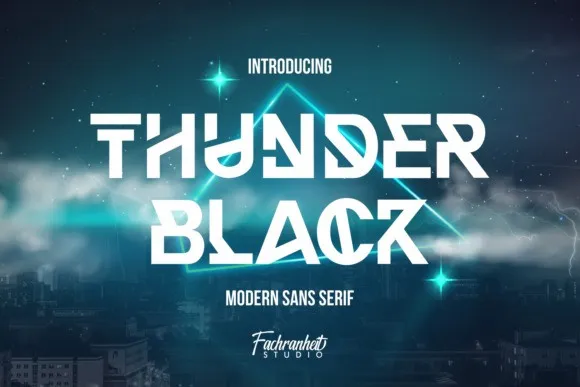
Thunder Black Font – Download Grátis
Esta é uma fonte de display minimalista e futurista criada pelo designer fachranheit. Ideal para projetos que exigem uma aparência única e moderna, esta fonte pode ser facilmente combinada com uma ampla gama de ideias, desde cartazes de filmes até folhetos e jogos, além de logotipos e letras tipo. Seu design clean e minimalista complementará perfeitamente os seus trabalhos, tornando sua produção ainda mais destacável. Para quem está procurando algo que seja inovador e destaca em qualquer mídia ou aplicação visual, a fonte “Thunder Black” é uma excelente opção. Suas linhas sóbrias e retas formam um padrão que é tanto atemporal quanto futurista, adaptável para uma infinidade de usos visuais e estilos. Seja você criando cartazes de filmes incrivelmente chamativos ou designando logotipos memoráveis, a “Thunder Black” fornecerá o formato perfeito para transformar suas ideias em realidade, elevando seu trabalho ao próximo nível.